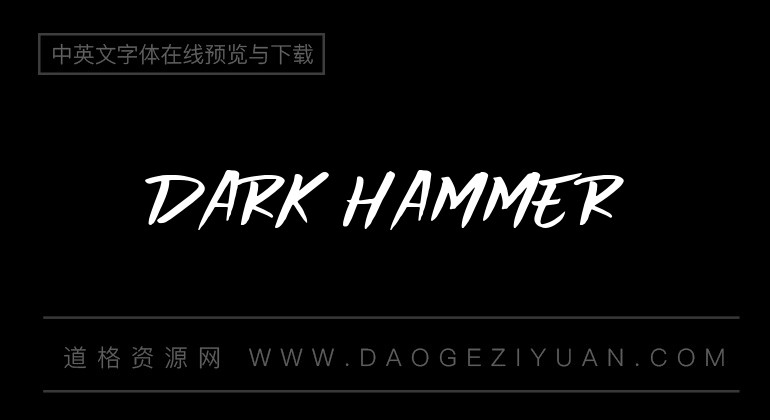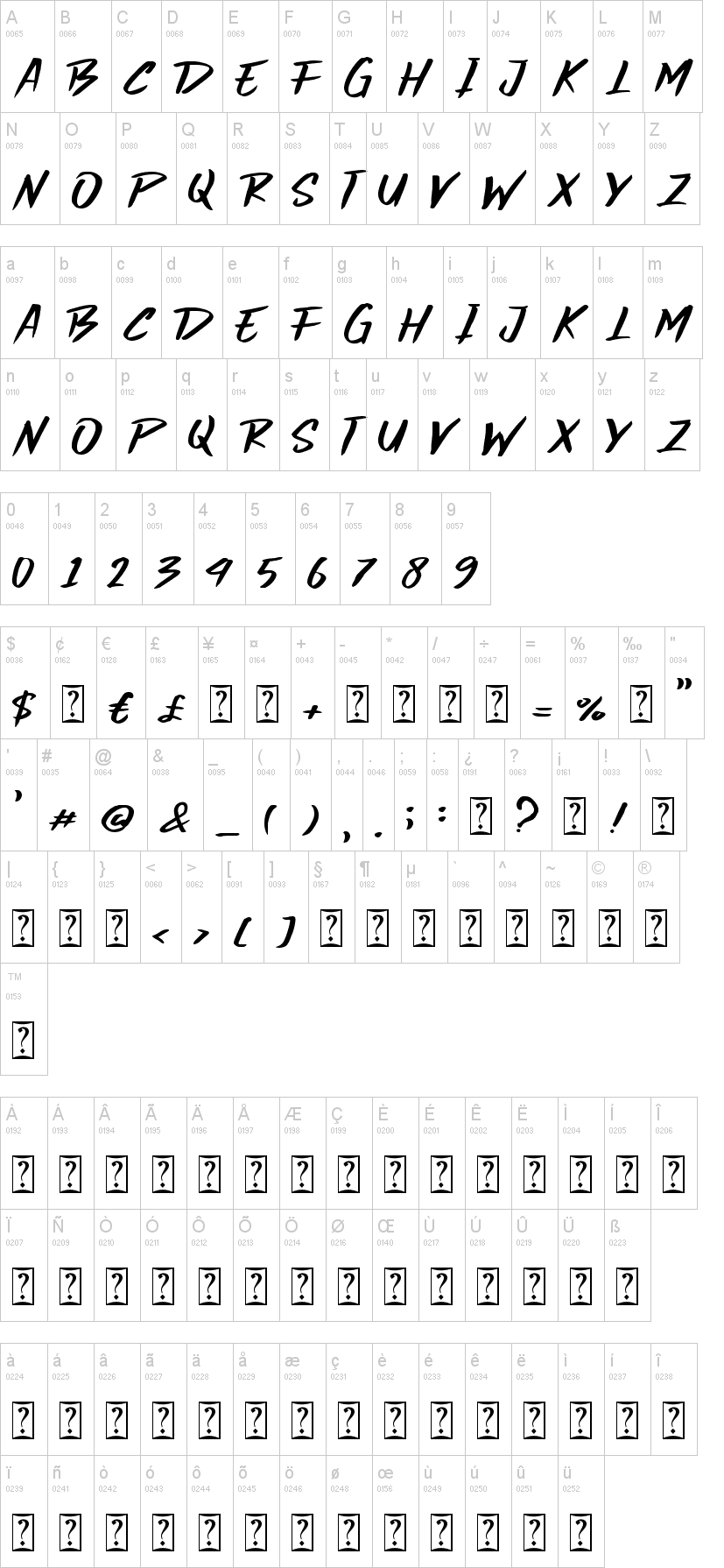
Dark Hammer 字体是一款粗体的字体,由Fontalicious设计,它有一种激进的外观,具有黑暗,钝重的外观。Dark Hammer字体可以用于标题,标签,标题等,它可以为您的项目带来一种独特的外观和感觉。它也可以用于印刷和网络媒体,它可以帮助您抓住读者的注意力并传达您的信息。内容介绍
Dark Hammer是一款非常不错的手写艺术字体,具有很好的视觉感,适合于文化类的宣传设计、商业类品牌的广告和产品包装设计以及个性化文字排版等较多场景。